LA LEGIBILIDAD DE LA TIPOGRAFÍA
El primer objetivo que debe tener un diseñador a la hora de trabajar con textos, es que éste sea legible, es decir, que facilite la lectura al posible receptor de ese trabajo. Cuando el diseñador domina las reglas que hacen que un texto sea más o menos legible o cuando es más importante la expresividad que el contenido textual, es cuando el diseñador podrá trabajar más libremente.
¿Cuáles son las reglas que debemos tener en cuenta para la legibilidad de los textos?
Es elemental analizar el tipo de diseño y mensaje que se quiere transmitir, según esto es importante elegir una fuente tipográfica, escoger un tipo de fuente acorde con el perfil del receptor o consumidor a quien va dirigido el mensaje. La tipografía en este caso debe apoyar los textos y complementar los elementos gráficos.
En primer lugar deberemos escoger caracteres que sean abiertos y bien proporcionados, con regularidad en los tipos y con remates clásicos. Los caracteres que contienen afectaciones estilísticas o irregularidades son menos legibles, por lo que son menos recomendables utilizarlos en bloques de textos y más adecuados para textos cortos o titulares.
Una vez elegida la tipografía con la que trabajaremos para hacer legible el trabajo, tendremos que tener en cuenta otros aspectos como el cuerpo con el que trabajaremos, la longitud de la línea o el interlineado. Cuando conseguimos que estos tres elementos armonicen “tipografía y su tamaño o cuerpo, longitud e interlineado”, se producirá una mayor facilidad de lectura, será más natural nuestro recorrido visual sobre el texto. Cuando variamos uno de estos aspectos en la tipografía, deberemos ajustar los otros para que la armonía se siga produciendo.
Deberemos elegir un cuerpo o tamaño de tipografía dependiendo de la finalidad y la importancia que queramos darle al texto. Cuando estamos hablando de un bloque de texto el tamaño idóneo debe estar entre 8 y 11 puntos, cuando nos referimos a otras finalidades del texto: titulares, subtítulos... los tamaños pueden ser muy variables.
En cuanto a la longitud de las líneas deberemos tener cuidado, ya que las demasiado largas producen aburrimiento en el lector y las demasiado cortas dificultan la lectura por el ritmo visual al que obliga con el cambio constante de línea de lectura. Dependiendo de qué tipo de textos o del tamaño del diseño nos tendremos que plantear distintas longitudes de línea, pero habitualmente se considera que el máximo de caracteres aceptados por línea es de sesenta a setenta.
Por otra parte el interlineado es un factor importante para que el lector pueda seguir correctamente la lectura sin equivocarse de línea o cansar la vista. Es el espacio vertical entre las líneas de texto. Como regla general, el interlineado debe ser aproximadamente un 20% mayor que el tamaño de la fuente. Por ejemplo un interlineado de 12 puntos es correcto para un texto de 10 puntos.
Pero siempre debemos tener en cuenta que los requerimientos varían según el texto y la fuente.
EFECTO DE LAS RELACIONES ENTRE SIGNOS
La legibilidad tipográfica estudia el efecto de las relaciones entre signos, ya que ningún lector lee signos aislados. Los elementos que lee son los naturales en que se agrupa nuestro sistema de escritura, a los que además está acostumbrado. Por ello se toma la palabra (que aparece en la escritura como una entidad visual) como la unidad de lectura.
La psicología de la lectura depende de numerosos factores. Entre ellos figuran los siguientes:
1. El ojo no puede desplazarse sin saltos sobre un texto impreso.
2. Sólo en los puntos de fijación se tiene pleno foco.
3. El reconocimiento de muchas palabras se da cuando están borrosas.
4. En la visión de colores, sólo las ondas medias (amarillos y verdes) quedan bien enfocadas en la retina.
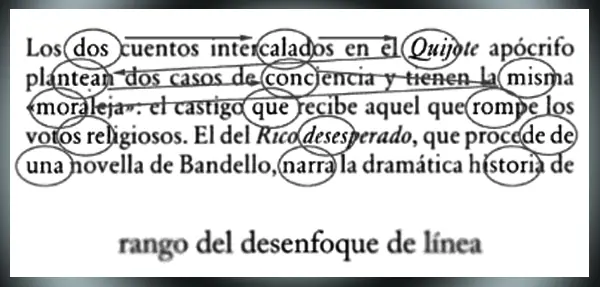
La Figura muestra, en un símil, lo que se denomina «rango de desenfoque de línea», es decir, el gradiente que va del foco al fuera de foco a lo largo de la línea de lectura, considerando diversos puntos de fijación. El lector mismo lo puede comprobar observando que, si mira a un extremo de una línea y no desplaza el ojo, lo más probable es que sea incapaz de leer palabras situadas en el otro extremo de la línea.
ELECCIÓN DE LA PALETA DE FUENTES
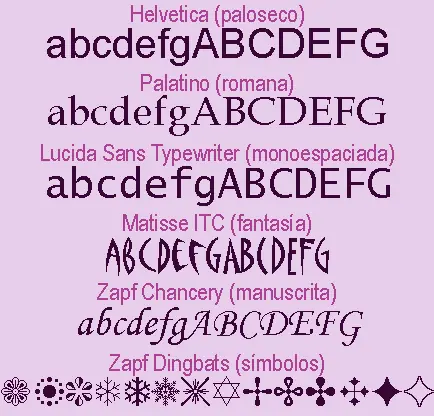
Tal como preparamos una paleta de colores para usar en un diseño o pintura, también podemos escoger un grupo de fuentes que vaya bien para un determinado trabajo. Una paleta típica contiene:
Todo diseñador debe tener la habilidad de analizar, explorar y reconocer las características conceptuales, formales, históricas y técnicas de los diferentes tipos de letras. Cada familia tipográfica tiene sus propias características y su propia personalidad, que permiten expresar diferentes notas visuales, unas más fuertes y otras más sutiles, unas más refinadas y otras más toscas, unas más geométricas y otras más orgánicas, por lo que la selección de las familias tipográficas a usar en una composición debe hacerse con un amplio sentido de la responsabilidad.
Para lograr una composición tipográfica adecuada, es necesaria una correcta selección de las familias tipográficas a utilizar, teniendo en cuenta su legibilidad, sus proporciones, el contraste entre los trazos gruesos y delgados, la existencia del remate o su falta, su inclinación y su forma.
La elección del tipo más adecuado depende en gran medida del tipo de mensaje al que va enfocada la composición. En algunos casos necesitaremos un tipo de letra refinada, elegante o delicada, mientras que en otros necesitaremos letras sobrias, macizas y sin ningún tipo de remilgos.
En general, las familias de origen romano, con serifas de pie, funcionan mejor como tipo de lectura en imprenta. Por el contrario, las de palo seco o sin serifas, dan mejor resultado en monitores y pantallas, sobre todo cuando hablamos de resoluciones bajas.
El factor más determinante sobre la elección de una fuente debe ser su legibilidad, propiedad derivada del diseño mismo de los tipos de letra, especialmente importante para textos largos. Para bloques de texto más cortos tenemos mayor libertad de elección, y para los títulos podemos emplear la fuente que queramos, en función del espíritu del documento y la sensación que nos interese crear.
Asociación fuente época
Una buena estrategia de trabajo es preparar una paleta de fuentes con una letra serif para el texto, una letra sans para los títulos y subtítulos, con tamaños mayores, otra para los pies de foto, resúmenes, citas y notas, de menor tamaño, y tal vez, una letra especial para el título principal. Es una fórmula que es simple y efectiva, que evita la mezcla de diferentes fuentes de palo seco juntas o diferentes letras serif juntas, combinaciones que raramente funcionan.
Algunas tipografías tienen versión sans y versión serif y suelen formar una perfecta combinación: por ejemplo, la forma serif para el texto y la sans para el resto. Con fuentes diferentes, es cuestión de probar.
La fuente elegida para el texto puede incluir, naturalmente, la variante cursiva y en negrilla. Ambas deben emplearse sólo para enfatizar partes del documento, no en fragmentos extensos.
Conviene evitar lo que ya está muy visto. Una fuente que todo el mundo usa hace que nuestros documentos sean indistinguibles, un producto clónico de los demás. Fuentes como Arial (Helvetica), Courier y Times New Roman son tan frecuentes que convierten un documento en algo anodino, sin impacto visual. Como alternativa hay fuentes que, siendo básicamente del mismo tipo, sacarán del anonimato y aburrimiento a los textos que preparemos.
Las combinaciones son de los siguientes tipos de letras:
Helvética / Garamond
Caslon / Univers
Frutiger / Minion
Futura / Bodoni
Garamond / Futura
Gill Sans / Caslon
Minion / Gill Sans
Univers / Caslon
Bodoni / Futura
Myriad / Minion
Avenir / Warnock
Caslon / Franklin Gothic
FF Din / Baskerville
Trade Gothic / Clarendon
Baskerville / Univers
Akzidenz Grotesk / Garamond
Clarendon / Trade Gothic
Franklin Gothic / Baskerville
Warnock/Univers
COLOR DE LA FUENTE TIPOGRÁFICA
Cada color tiene un significado determinado, estos deben estar en armonía con los colores utilizados en los elementos gráficos en la diagramación de la pieza. Los colores de la tipografía deben generar suficiente contraste, para llamar la atención del lector y darle además el justo equilibrio visual necesario entre texto y tipografía.
Diseñar con tipos y colores es un gran reto, ya que cuando los colores y los tipos aúnan sus fuerzas, el riesgo de errar se acentúa; aunque también es cierto que la combinación de tipos y color hace que se resalte los atributos visuales y expresivos de la tipografía.
En la elección del color uno de los aspectos que debemos no olvidar es la legibilidad tipográfica.
Cuando se combinan tipos y color, el equilibrio entre estas características es crucial.
Los colores azules y naranja, complementarios totalmente saturados, ofrecen un contraste tonal pleno, pero cuando lo aplicamos a tipo y fondo los bordes de las letras tienden a oscilar y complica la lectura del texto. Esto ocurre porque ambos colores poseen un brillo que rivaliza entre sí y que reclaman atención propia. La solución es suavizar o acentuar uno de los tonos haciendo que su valor pase a ser claro u oscuro.
El color, aplicado discretamente a algunas partes del texto, puede mejorar mucho su legibilidad, darle un mayor peso visual e incluso crear la impresión de mayor variedad de fuentes. Un ligero toque de color en los subtítulos, o remarcando una cita, es un recurso muy útil y elegante, pero hacer un collage de colores en una página de texto que pretende ser serio o informativo pone en evidencia un mal gusto y un escaso sentido común.
Cuando tenemos que buscar un color para asociar a un tipo, lo primero que deberemos de examinar son los objetivos del trabajo que tenemos que realizar y el público al que va dirigido. No es lo mismo un cartel destinado a anunciar el último disco de un grupo musical que un folleto sobre planes de pensiones de un banco. Ambos temas son totalmente diferentes y están destinados a públicos con preferencias y necesidades distintas.
Uno de los factores más importante de los textos, que influye sobremanera en la legibilidad de los mismos, es el contraste entre estos y el fondo sobre el que se sitúan. Un contraste adecuado hace que los textos se lean bien y que su lectura no canse al lector, condición muy importante en obras de contenido textual importante. Si el tipo se disminuye en tamaño, debe incrementarse la fuerza de contraste de color.
Estamos acostumbrados a ver tipos negros sobre papel blanco, y tradicionalmente esta combinación es la más legible. Además muchos tipos se han diseñado para ser leídos como letras negras sobre fondo blanco y ofrecen una óptima legibilidad impresos de este modo.
En el momento en que se añade color al tipo o al fondo, se altera la legibilidad del texto. En consecuencia, la tarea del diseñador es combinar las propiedades del tipo y el color para multiplicar su potencial comunicativo. Estos dos elementos pueden dar vida a un texto que, de otro modo, fracasaría en su vertiente comunicativa.
Para alcanzar la óptima legibilidad cuando se diseña con tipos y color se han de sopesar cuidadosamente las tres propiedades del color (tono, valor e intensidad) y determinar el contraste apropiado entre las letras y su fondo. Podemos usar contrastes de tono (cálidos y fríos), contrates de valor (luminoso y oscuro) o contrastes de saturación (vivos y apagados).
Los colores azules y naranja, complementarios totalmente saturados, ofrecen un contraste tonal pleno, pero cuando lo aplicamos a tipo y fondo los bordes de las letras tienden a oscilar y complica la lectura del texto. Esto ocurre porque ambos colores poseen un brillo que rivaliza entre sí y que reclaman atención propia. La solución es suavizar o acentuar uno de los tonos haciendo que su valor pase a ser claro u oscuro.
Un texto de color amarillo sobre fondo blanco perdería importancia, ya que, no resaltaría al ser los dos colores claros, sin embargo, si el color de fondo es negro, el amarillo cobraría fuerza. Según algunos estudios, la letra más legible es la negra sobre fondo amarillo.
Por otra parte, si dos colores análogos están demasiado cerca en el círculo cromático y no aportan suficiente contrate de tono o valor, deberían reajustarse para agudizar dicho contraste. Un buen principio es coger colores que no estén directamente enfrentados ni estén demasiado próximos en el círculo cromático. Deben buscarse colores compatibles, pero también colores que difieran en valor e intensidad.
Tendremos que tener también en cuenta las cualidades y características de cada tipo, ya que un tipo muy fino o estrecho, o una letra de trazo puede parecer muy débiles o ilegibles si los tonos son muy similares o si los valores están demasiado próximos. Por lo tanto, debe de existir el contraste suficiente para proteger la fidelidad de las letras.
Si el contraste de colores no basta por sí solo para destacar el tipo sobre el fondo, pueden añadirse perfiles y sombras. De todas formas no es recomendable utilizar estos efectos en los bloques de texto, pues en términos de legibilidad sería más perjudicial que beneficioso. Los mejores resultados se consiguen con tipos grandes o en titulares.
Otra solución, cuando el contraste de color es escaso o cuando debe imprimirse en color un gran fragmento textual, es configurar correctamente los espaciados, pues favorecen la legibilidad.
Empleando tramas podemos enriquecer la variedad cromática de un texto sin tener que añadir colores adicionales. Las tramas resultan especialmente útiles en trabajos de impresión con uno o dos colores.
Tendremos que tener también en cuenta las cualidades y características de cada tipo, ya que un tipo muy fino o estrecho, o una letra de trazo puede parecer muy débiles o ilegibles si los tonos son muy similares o si los valores están demasiado próximos. Por lo tanto, debe de existir el contraste suficiente para proteger la fidelidad de las letras.
COLOR TIPOGRÁFICO
Otro concepto que debemos conocer es el llamado "color tipográfico": una ilusión óptica creada por las propias proporciones y las formas de los diseños tipográficos que nos da la sensación de distinto color aunque esté impreso en el mismo color. Aunque las palabras estén impresas en el mismo color, cada una de ellas puede poseer un tono distinto debido a las características propias de sus diseños tipográficos.
Cuando hablamos de color tipográfico estamos entrando en el campo de las ilusiones ópticas: todos los signos de una mancha textual pueden estar impresos en un mismo tono de negro absoluto y sin embargo crear una superficie gris. Así, un mismo cuerpo puede producir un efecto visual muy diferente según el espaciado elegido entre los signos y entre líneas.
El negro, entonces, crea para el ojo toda la gama de grises.
Pero ese mismo negro produce otro efecto colateral que no debe ser ignorado: un valor negro, por pequeño que sea, “consume” el blanco; lo elimina y se coloca a un nivel inferior que la superficie blanca: existen tantos grados de relieve en profundidad como tonalidades de gris posibles.
De esta manera, valor de gris y profundidad son dos resultados óptico-formales ineludibles en cualquier mancha textual, y deberán ser tenidos en cuenta en todo trabajo tipográfico. Aún si trabajamos con una única familia, son numerosas las variables que se deben controlar y que, con un mínimo cambio en alguna de ellas, el color tipográfico indefectiblemente será modificado. Tanto el peso visual de la fuente en sí misma (roman, bold, extra bold, black, medium, light, extra light, condensed o extended), como su cuerpo, su interletra o interlínea producen estas alteraciones.
Una acertada decisión de grises, dependiendo de las categorías textuales con las que deseemos trabajar, nos asegurará fuerza formal y dinamismo en nuestra puesta tipográfica.
CÓMO IMPACTA EL COLOR
Los colores pueden dividirse en dos grupos:
Los colores cálidos van desde el rojo al amarillo, y son colores muy impactantes, ya que destacan mucho sobre un fondo. El rojo o el naranja son colores muy vistosos y llamativos, por este motivo se usa el color rojo en los semáforos y muchas señales de peligro. Los colores fríos, son los verdes hasta los azules, tienen la característica de que son muy relajantes. Se utilizan en la decoración infantil, centros de estudio, hospitales Colores fríos, colores fríos.
TIPOGRAFÍA Y PSICOLOGÍA DEL COLOR
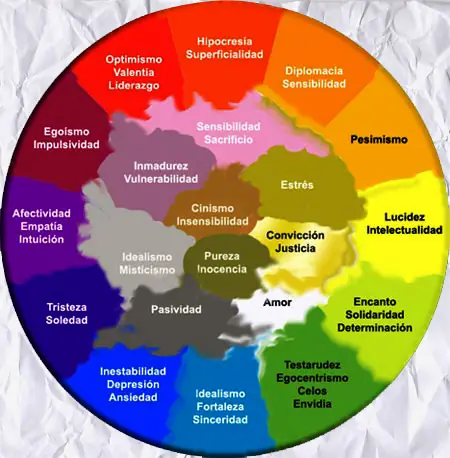
Cada color ejerce sobre la persona que lo observa una triple acción:
- Impresiona al que lo percibe, por cuanto que el color se ve, y llama la atención.
- Tiene capacidad de expresión, porque cada color, al manifestarse, expresa un significado y provoca una reacción y una emoción.
- Construye, todo color posee un significado propio, y adquiere el valor de un símbolo, capaz por tanto de comunicar una idea. Los colores frecuentemente están asociados con estados de ánimo o emociones.
Los colores nos afectan psicológicamente y nos producen ciertas sensaciones. Debemos dejar constancia que estas emociones, sensaciones asociadas corresponden a la cultura occidental, ya que en otras culturas, los mismos colores, pueden expresar sentimientos totalmente opuestos por ejemplo, en Japón y en la mayor parte de los países islámicos, el color blanco simboliza la muerte.
El color Blanco
Es el que mayor sensibilidad posee frente a la luz. Es la suma o síntesis de todos los colores, y el símbolo de lo absoluto, de la unidad y de la inocencia, significa paz o rendición. Mezclado con cualquier color reduce su croma y cambia sus potencias psíquicas, la del blanco es siempre positiva y afirmativa. Los cuerpos blancos nos dan la idea de pureza y modestia. El blanco crea una impresión luminosa de vacío, positivo infinito.
El color negro
Símbolo del error, del mal, el misterio y en ocasiones simbólica algo impuro y maligno. Es la muerte, es la ausencia del color. También transmite nobleza y elegancia.
Color gris
Es el centro de todo ya que se encuentra entre la transición entre el blanco y el negro, y el producto de la mezcla de ambos. Simboliza neutralidad, indecisión y ausencia de energía. Muchas veces también expresa tristeza, duda y melancolía. El color gris es una fusión de alegrías y penas, del bien y del mal. Da la impresión de frialdad metálica, pero también sensación de brillantez, lujo y elegancia.
Simbología del color amarillo y rojo
Por ejemplo una invitación de un color brillante debe evocar la imagen del mismo valor, sino y en caso opuesto conseguiríamos un efecto contraproducente, transmitiendo la sensación de falsificación. Si es de color oro, la imagen debe combinar en concordancia con el color expuesto, para que se tenga una visión agradable y equilibrada de la presentación.
El color amarillo:
Es el color más intelectual y puede ser asociado con una gran inteligencia o con una gran deficiencia mental; Van Gogh tenía por él una especial predilección, particularmente en los últimos años de su crisis. Este primario significa envidia, ira, cobardía, y los bajos impulsos, y con el rojo y el naranja constituye los colores de la emoción. También evoca satanismo (es el color del azufre) y traición. Es el color de la luz, el sol, la acción, el poder y simboliza arrogancia, oro, fuerza, voluntad y estimulo.
Mezclado con negro constituye un matiz verdoso muy poco grato y que sugiere enemistad, disimulo, crimen, brutalidad, recelo y bajas pasiones. Mezclado con blanco puede expresar cobardía, debilidad o miedo y también riqueza, cuando tiene una leve tendencia verdosa. Los amarillos también suelen interpretarse como joviales, afectivos, excitantes e impulsivos. Están relacionados con la naturaleza. Psicológicamente se asocia con el deseo de liberación.
El color rojo:
Se lo considera con una personalidad extrovertida, que vive hacia afuera, tiene un temperamento vital, ambicioso y material, y se deja llevar por el impulso, más que por la reflexión. Simboliza sangre, fuego, calor, revolución, alegría, acción, pasión, fuerza, disputa, desconfianza, destrucción e impulso, así mismo crueldad y rabia. Es el color de los maniáticos y de Marte, y también el de los generales y los emperadores romanos y evoca la guerra, el diablo y el mal. Como es el color que requiere la atención en mayor grado y el más saliente, habrá que controlar su extensión e intensidad por su potencia de excitación en las grandes áreas cansa rápidamente.
Mezclado con blanco es frivolidad, inocencia, y alegría juvenil, y en su mezcla con el negro estimula la imaginación y sugiere dolor, dominio y tiranía. Expresa sensualidad, virilidad y energía, considerado símbolo de una pasión ardiente y desbordada. Por su asociación con el sol y el calor es un color propio de las personas que desean experiencias fuertes.
El color naranja:
Es un poco más cálido que el amarillo y actúa como estimulante de los tímidos, tristes o linfáticos. Simboliza entusiasmo y exaltación y cuando es muy encendido o rojizo, ardor y pasión. Utilizado en pequeñas extensiones o con acento, es un color utilísimo, pero en grandes áreas es demasiado atrevido y puede crear una impresión impulsiva que puede ser agresiva. Posee una fuerza activa, radiante y expresiva, de carácter estimulante y cualidad dinámica positiva y energética. Mezclado con el negro sugiere engaño, conspiración e intolerancia y cuando es muy oscuro, opresión.
El color azul:
Simboliza, la profundidad inmaterial y del frío.
La sensación de placidez que provoca el azul es distinta al de la calma o del reposo terrestre propio del verde.
Se lo asocia con los introvertidos o personalidades reconcentradas o de vida interior y está vinculado con la circunspección, la inteligencia y las emociones profundas.
Es el color del infinito, de los sueños y de lo maravilloso, y simboliza la sabiduría, amistad, fidelidad, serenidad, sosiego, verdad eterna e inmortalidad. También significa descanso. Mezclado con blanco es pureza, fe, y cielo, y mezclado con negro, desesperación, fanatismo e intolerancia. No fatiga los ojos en grandes extensiones
El color violeta
El violeta, es el color de la templanza, la lucidez y la reflexión. Transmite profundidad y experiencia. Tiene que ver con lo emocional y lo espiritual. Es místico, melancólico y se podría decir que también representa la introversión. En su variación al púrpura, es realeza, dignidad, suntuosidad. Mezclado con negro es deslealtad, desesperación y miseria. Mezclado con blanco: muerte, rigidez y dolor.
Color verde
Es un color de extremo equilibrio
Se lo asocia con las personas superficialmente inteligentes y sociales que gustan de la vanidad de la oratoria y simboliza la primavera y la caridad.
Incita al desequilibrio y es el favorito de los psiconeuróticos porque produce reposo en el ansia y calma, tranquilidad, también porque sugiere amor y paz y por ser al mismo tiempo el color de los celos, de la degradación moral y de la locura.
Significa realidad, esperanza, razón, lógica y juventud. Aquellos que prefieren este color detestan la soledad y buscan la compañía. Mezclado con blanco expresa debilidad o pobreza. Sugiere humedad, frescura y vegetación, simboliza la naturaleza y el crecimiento. La persona que destaca por el uso del color verde, quiere ser respetada y competente.
Las tipografías doradas o plateadas
Sobre fondos oscuros nos evocan elegancia y sofisticación, y son muy adecuadas, si se trata de un proyecto donde se debe incluir el lujo, la elegancia o poder.
El blanco, gris y negro, no pueden incluirse en los grupos de cálidos y fríos. Los colores primarios (Magenta, Cian y Amarillo) se utilizan en productos infantiles, porque aportan alegría y juventud. Y además estos colores, en los niños les recuerdan a los dulces.
Los tonos marrones, tostados cremas y ocres.
Representan añoranza y son perfectos para representar productos naturales y clásicos. También para los productos de vinos (reposados, añejos, etc.) En publicidad se emplea en anuncios en blanco y negro o escala de grises, para resaltar el producto o elemento protagonista.